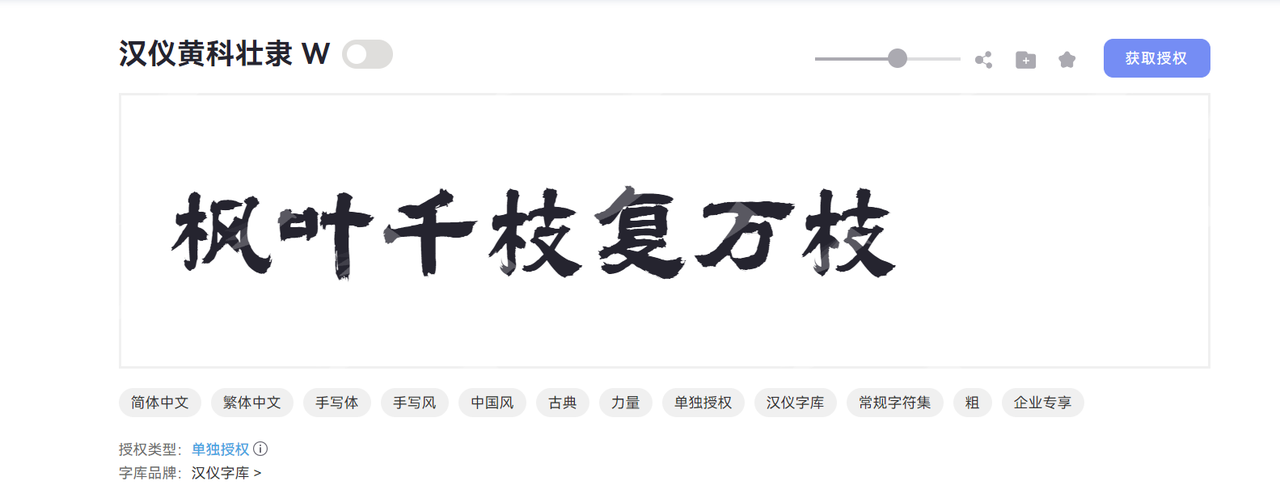
近些年设计领域对于字体的关注度逐渐加深,而且越发注重手写字体的表达。从数字内容到活动海报、文创设计到品牌 logo,手写字体凭借其独特的艺术感和人情味儿成为了提升设计质感的核心元素。相较于其他的字体,手写字体更能拉近设计师与观众的距离,能让作品更加有温度。然而,我周围的设计师朋友们经常找不到合适的手写字体资源,即使非常想用,但无从下手。本文精选 10 款来自字由官网的高级不撞款的手写字体模板,免费商用,一键即可应用到各类设计软件中,解决字体选择困难,帮助你打造 2026 年爆款设计作品!
1.点字浩蔓体
字体风格:用笔结字自由,欢乐,张弛有度,有意识的突出节奏感律动美,彰显豪放力量但又带着一丝活泼的风格。
字体特点:主要以行书草书为基础,笔画链接自然,粗细变化富有韵律。部分字的笔画末端自带锋芒,增强了书法的真实感,显得更加自然飘逸。
适配场景:古风海报、文创书签、茶类品牌包装、历史题材广告。
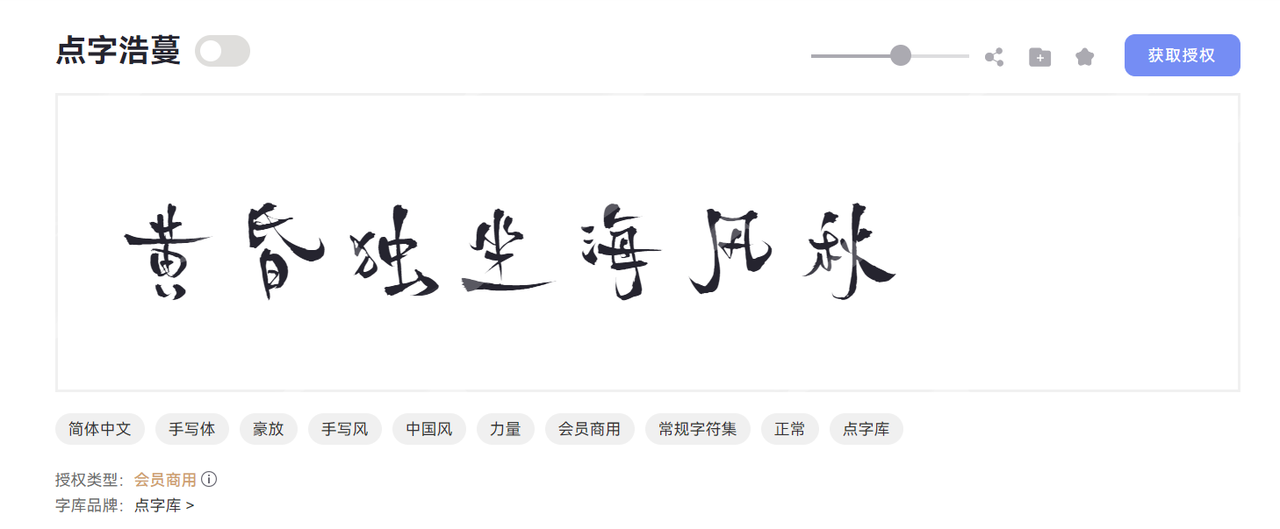
2.汉仪黄科壮隶 W 体
字体风格:以中国风为核心,融合古典隶书底蕴与现代设计审美,兼具力量感与艺术表现力,呈现“遒劲刚健、古意盎然”的视觉效果。
适配场景:民俗节庆设计、古典书籍封面、古风餐厅门头
3.字由面包树体
字体风格:风格轻松活泼,用笔上轻重相互穿插,视觉上给人舒朗而又紧凑,同时又呈现出可爱有趣的气质。
字体特点:字体质感偏软笔,形似面包树。笔画较为柔和,笔画边缘无尖锐锋芒,结构舒展匀称,而且整体笔画厚重饱满,增强了视觉亲和力。
适配场景:童话主题文创、儿童画本/插画、母婴品牌、甜品海报
4.溅墨版荒草体
字体风格:毛笔草书融合泼墨的特效,传递出书写体的雄浑气势以及灵动性,突破了刻板框架。 字体特点:笔画连贯,周围自带墨点特效,模拟出了真实的泼墨效果。
适配场景:山水景区宣传、诗词展览、中秋节海报
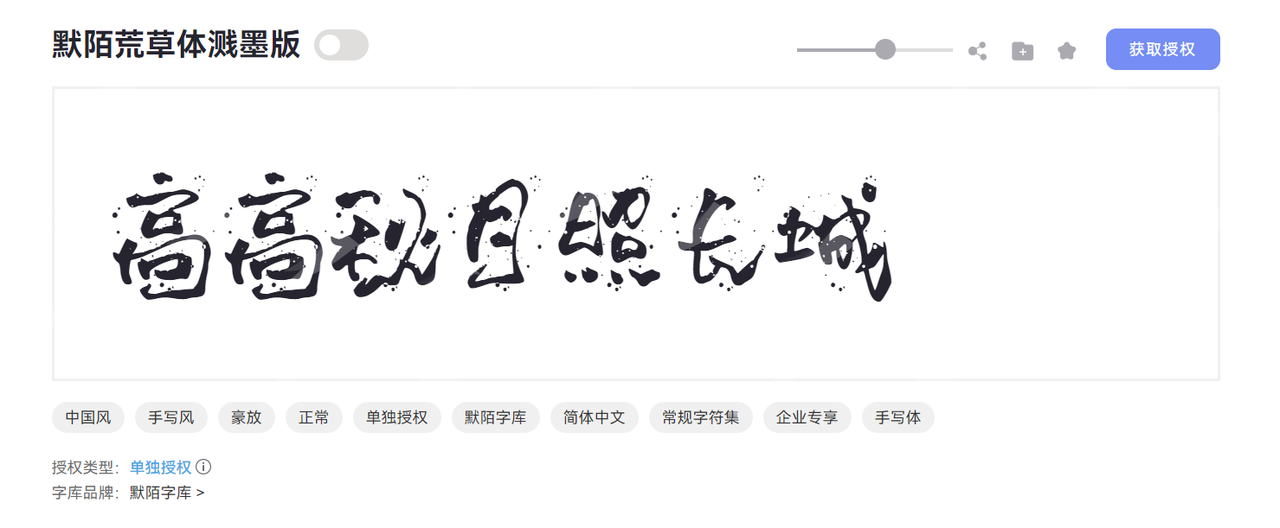
5.点字浩魂体
字体风格:一款中国风力量感手写体,以复古笔触碰撞现代设计,尽显随性洒脱、豪放不羁的书写魅力。
字体特点:字形方正稳健,重心居中平衡,以行草为核心,融合了隶书的厚重感。笔型利落直角勾勒,方头笔画刚劲如刀刻,粗细均匀的线条中暗藏飞白肆意的笔触,锋芒毕露却不失结构严谨。
适配场景:力量感品牌 logo、古镇景区宣传海报、国风包装、复古海报
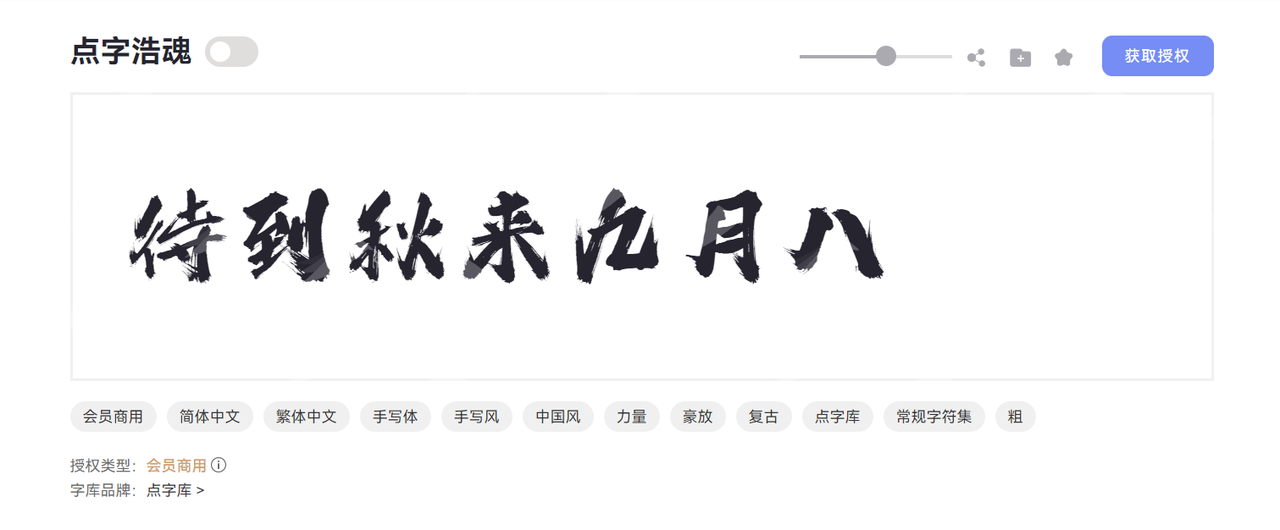
6.字由飘带体
字体风格:一款集传统韵味与现代风格于一身的创意字体,给人轻松灵动的视觉感受。
字体特点:这款字体拥有其独特的飘带形态笔画,为文字注入了生命与动感。以行书为基础,字形没有明显的方正框架,笔画融合了艺术化的连笔,整体连贯一气呵成,且可读性很强。
适配场景:文艺纪录片、汉服品牌、咖啡包装、古风展览
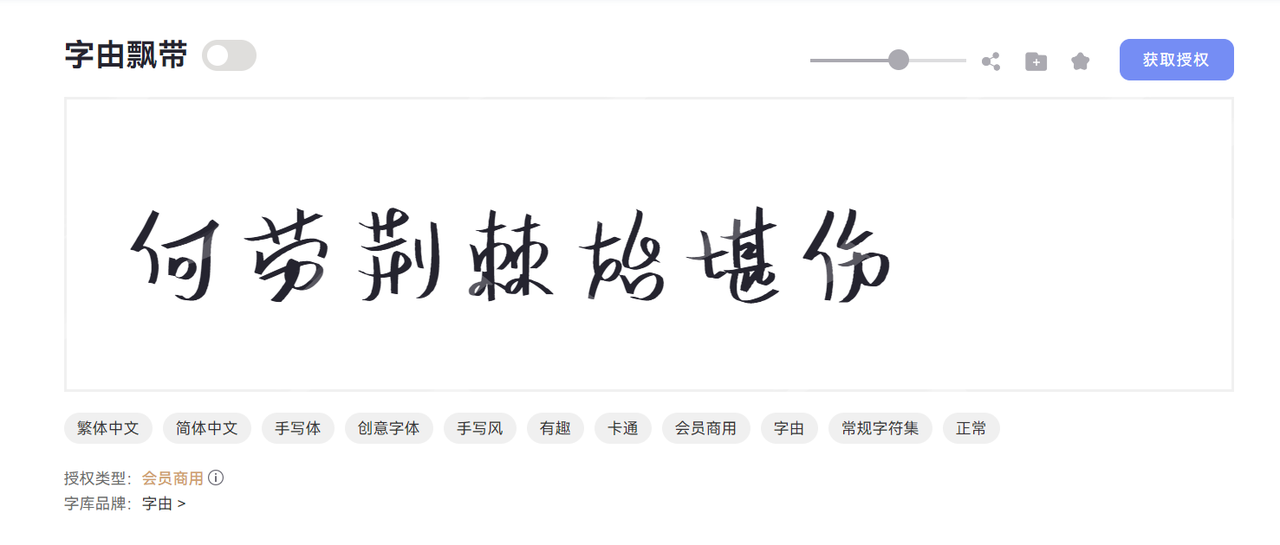
7.字由锦绣
字体风格:字由品牌推出的一款中国风手写体字体,以“繁花如锦,神采挥洒”为设计理念,融合古典韵味与豪放笔意,是兼具力量感与手写温度的商用优选。
字体特点:字形方正稳健,重心居中且中宫宽博,既保证了整体结构的舒展大气,又通过留白营造出从容的视觉节奏。笔画设计巧妙,方头起笔干净利落,笔画末端的卷曲装饰增添一份古典雅致。
适配场景:古典主题海报、诗词大会、国学讲座
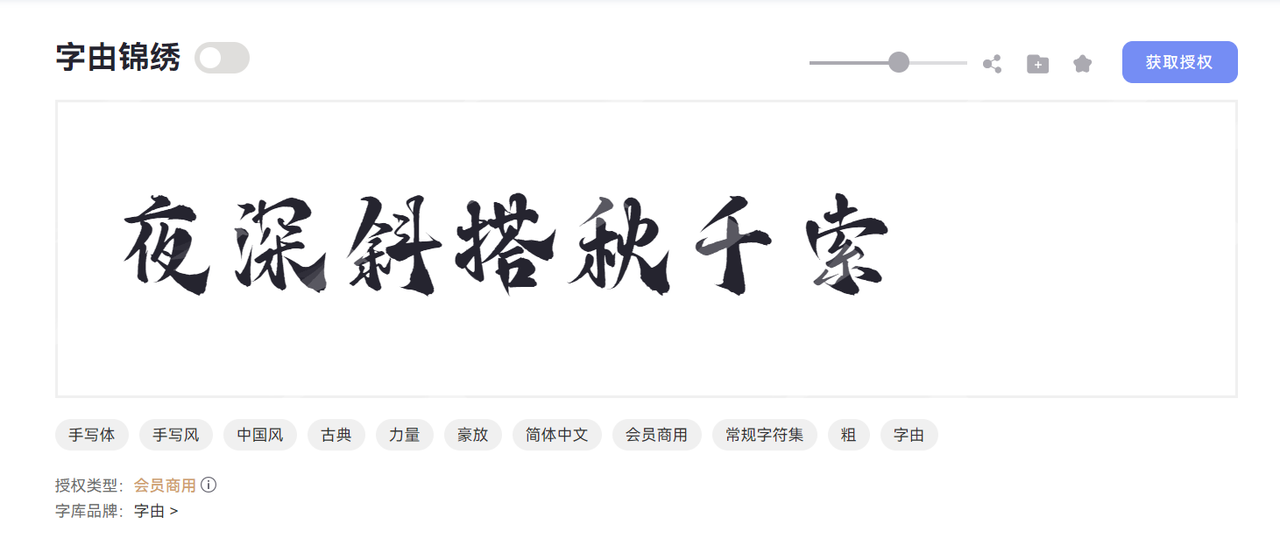
8.点字涂画体
字体风格:点字涂画主要以儿童涂鸦为基础,融合了卡通化以及中国风的元素,呈现出童趣且活泼的风格。
字体特点:字形结构整体以上下拉伸,笔画细长,字形拙朴,横竖规矩,在闭合的线条以黑色填充,让字形更具厚实感。字间距宽松,视觉上看起来轻松不局促,每个字都像是儿童随意涂鸦的变形,加强了可爱的感觉。
适配场景:涂鸦风文创、幼儿园海报、幼儿读物、萌宠展会
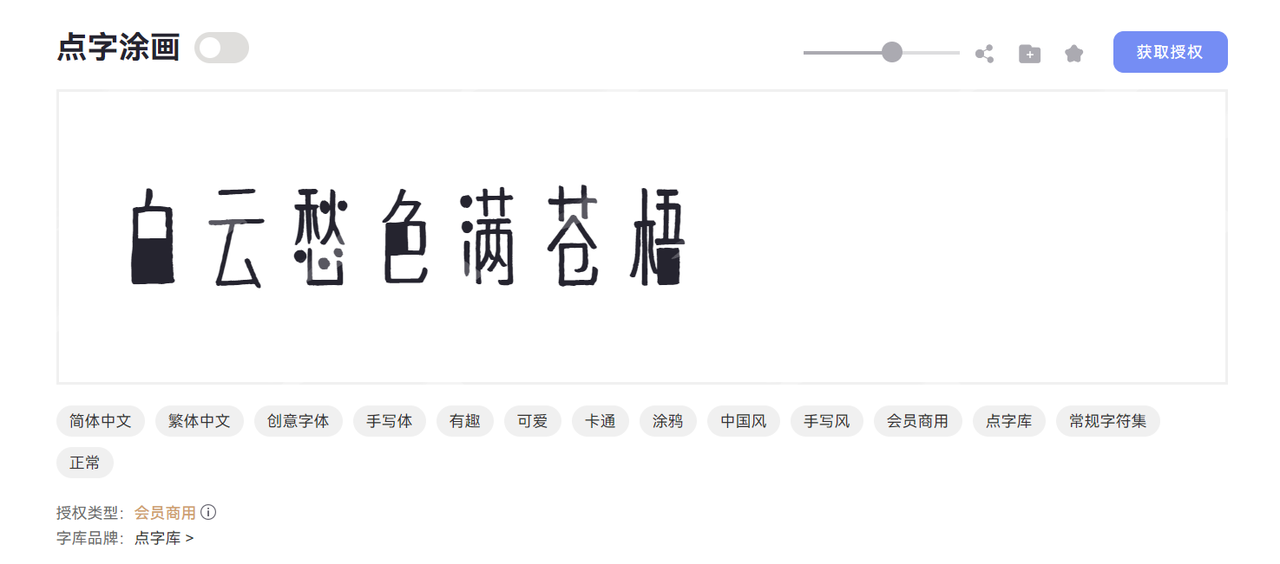
9.点字隶楷体
字体风格:一款融合楷书方整结构与隶书典雅体势的书法手写体,兼具中国风的古典韵味与手写笔触的力量感,为设计注入复古雅致的视觉张力。
字体特点:字形方正稳重,重心居中,中宫适中,画粗细均匀适中,连接多为断开,保留手写书法的自然呼吸感。笔型设计巧妙糅合双体精髓——楷书方头起笔的硬朗与隶书波磔的灵动并存,横画保留汉隶经典垂头起笔,撇捺小笔画增添弹性弧度,装饰元素细腻却不繁复,让每一笔都兼具力量感与韵律美。
适配场景:国潮文创、书法主题海报
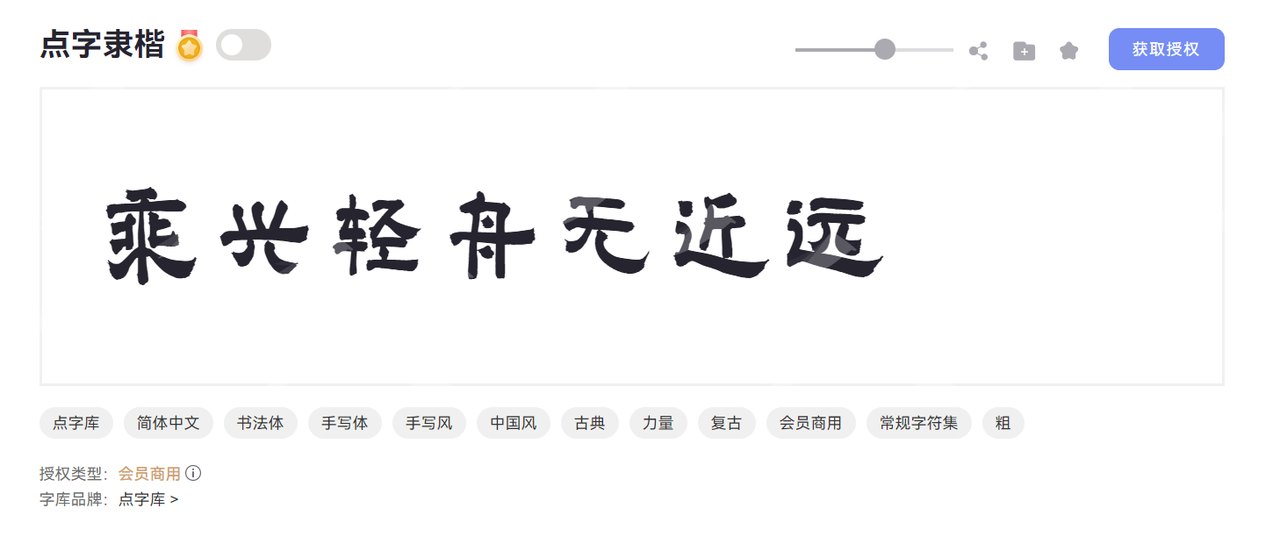
10.沐瑶软笔手写体
字体风格:一款兼具卡通趣味与端庄优雅气质的手写体字体,以灵动手写风为核心,卡通风格与手写趣味自然融合。
字体特点:修长的字型形态搭配居中的重心与适中的中宫,整体视觉平衡且舒展,既不过于紧凑也不显松散。笔型融入圆润弧度设计,圆头笔画搭配均匀的粗线条,让字体自带温暖柔和的质感。
适配场景:国风海报标题、国风手账